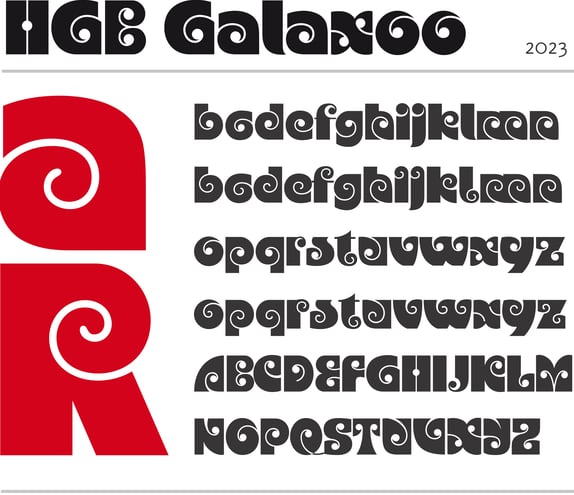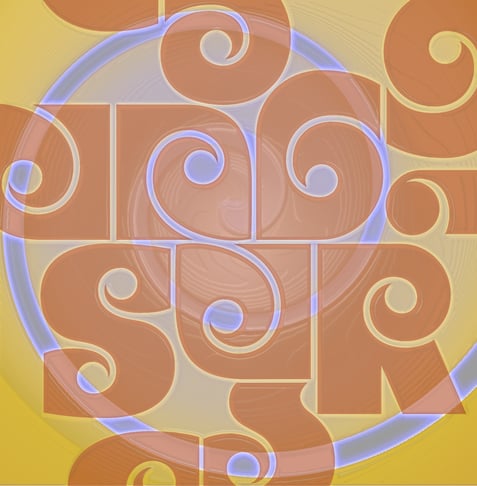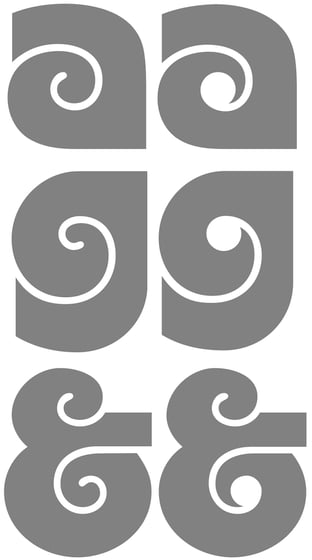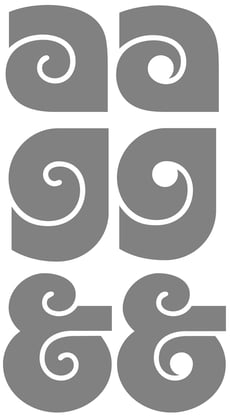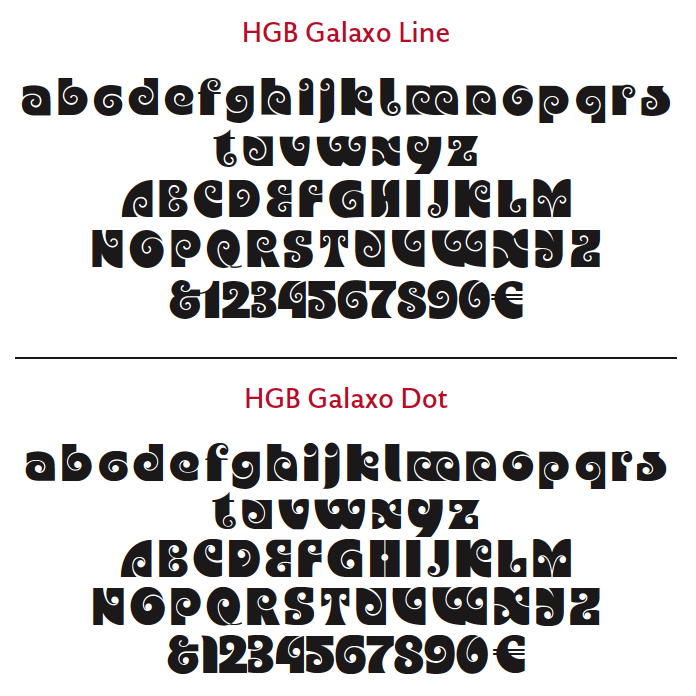
HGB Galaxo
Die HGB Galaxo ist eine Verneigung vor Othmar Motter (1927–2010), dem Vorarlberger Grafiker und Schriftentwerfer, der besonders in den 1970er-Jahren sehr eigenständige und perfekt ausgearbeitete Schriften gezeichnet hat. Aus einer Motter-Skizze für einen Schriftzug »Gamahl« habe ich ganz in seinem Sinne (Hoppala – daraus könnte man ein Alphabet machen!) eine vereinfachte Schriftform abgeleitet und alle notwendigen Zeichen entwickelt. Dabei haben sich zwei Formen ergeben: Dot und Line. Bei der Arbeit an diesen Formen und bei der Vertiefung in Motters Schriften wurde die Hochachtung vor der Akuratesse, mit der er seine Buchstaben (mit Tusche) gezeichnet hat, um so größer.